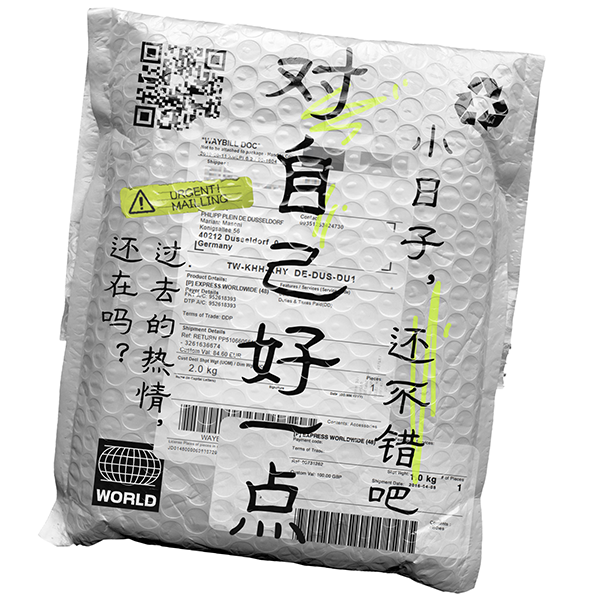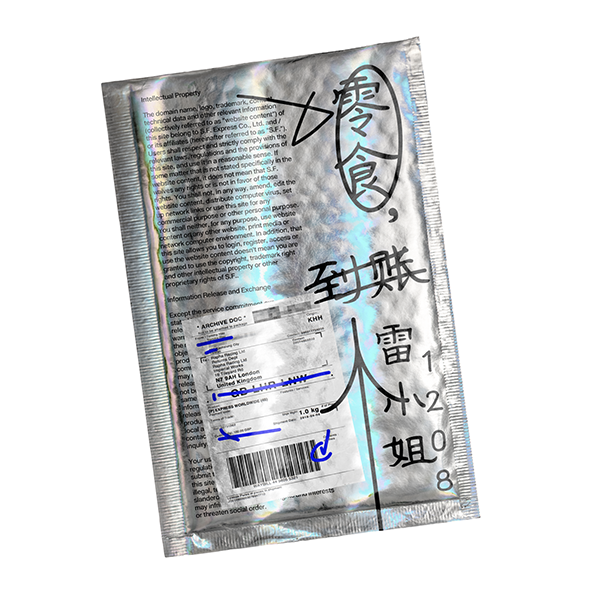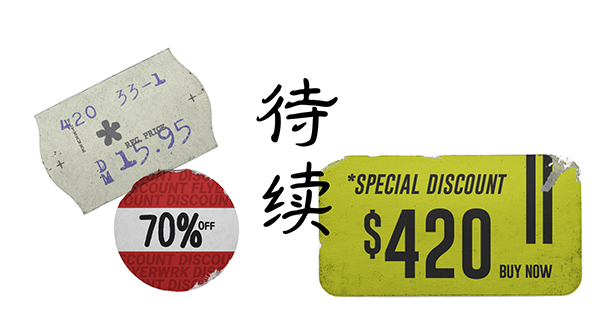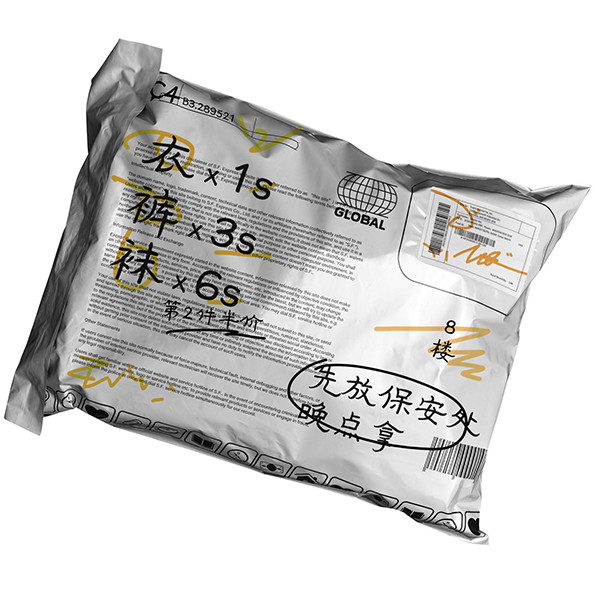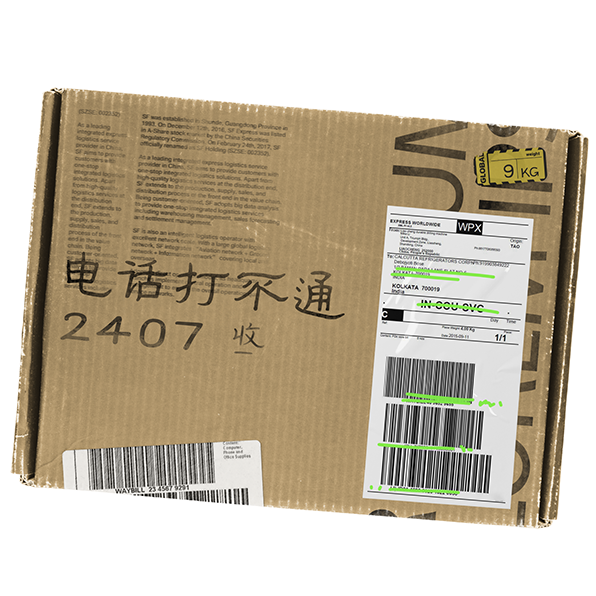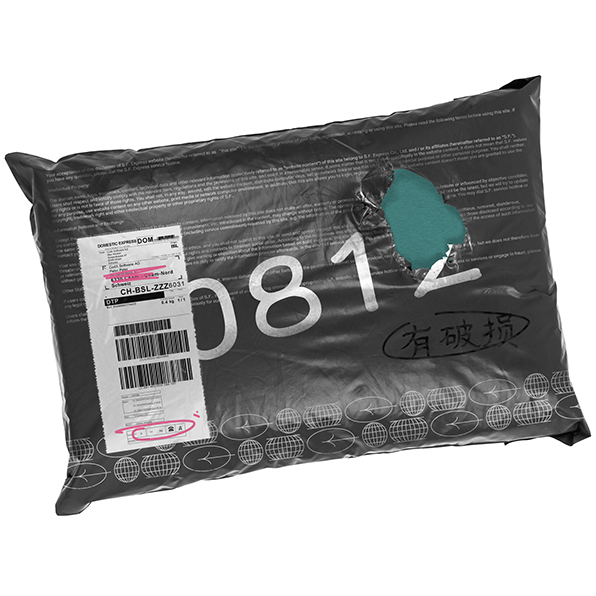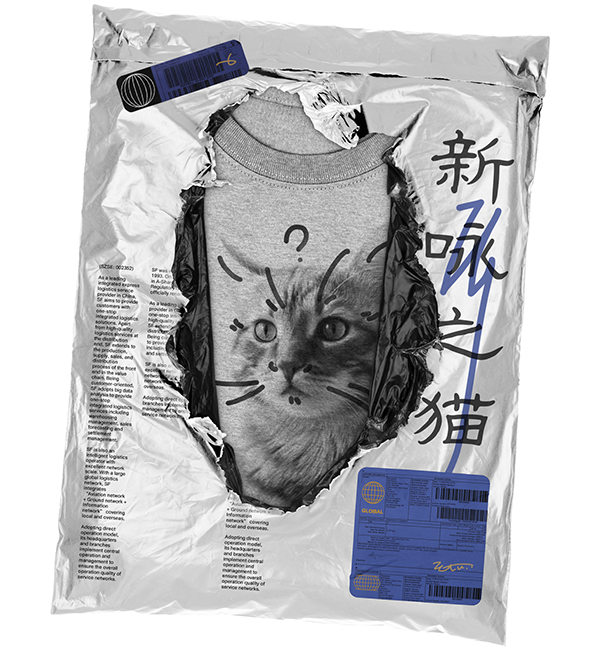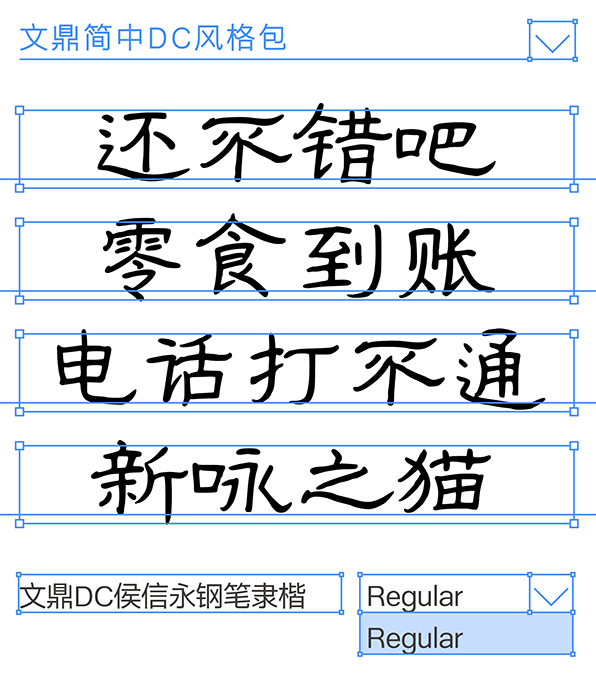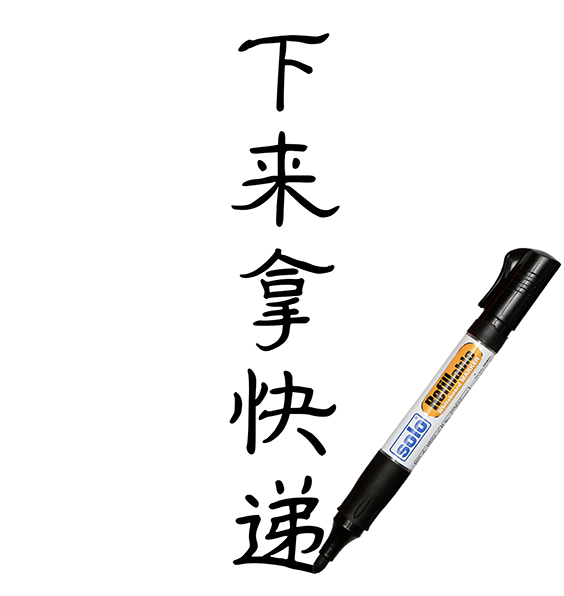
字体剧场 | 快递员的墨宝
今 天 的 白 日 梦,跟 “快 递” 有 关
双11的日子,即将来袭
网上购物的同时,
最苦恼的会是收到很多快递了吧?
然而,
今天,有一个快递员,
很喜欢在快递包裹上写字?
他的名字叫新咏~
“靓仔,下来拿快递”
一年下来,太多难以表达的故事和经历,
好好奖励一下“自给”
零食
肯定是必不可少的哟
一年为期,
大量换装备的时候来了
除了衣食住行,
还要有燃火起来的东西才行对了,
记得填对电话号码
天气变冷了
衣服还是要多备几件呢
好像都买够了?
或者用自己的“儿子”
定制一件衣服
侯信永钢笔隶楷
知名硬笔书法家 侯信永,他与文鼎字库合作开发的手写钢笔字型;他的创作来自于血脉相连的隶书与楷书,通过蚕头雁尾的隶书点缀,淡化了刚劲方严的正楷之气,交融出庄重秀逸的字韵,大气雅致的新面貌,点亮文字的新生命。期待《侯信永钢笔隶楷体》可以有机会遇见你,带给你不一样的文字情怀。
• 传统的剧场,主要指在演出戏剧的建筑空间。但随着科技进步,手机、电影、电视的发明与普及,剧场已经不单指是在实体的表演空间,剧场的形式充斥在大众生活之中的各种媒介,或许我们拥有一部手机,就是一个微型的剧场空间。
• 文鼎字库于 2020 年开始,以「虚拟的故事情节」作为字体剧场的出发点,发掘贴近现代生活的有趣话题,拟编成短暂的故事。透过Re-design的方式将与话题息息相关的东西进行重现,并将文鼎的字体设计产品参与其中,共同探索字体设计在日常生活中的可能性、趣味性、实验性。
• 希望让读者察觉,原来,字体的应用可以如此有趣。